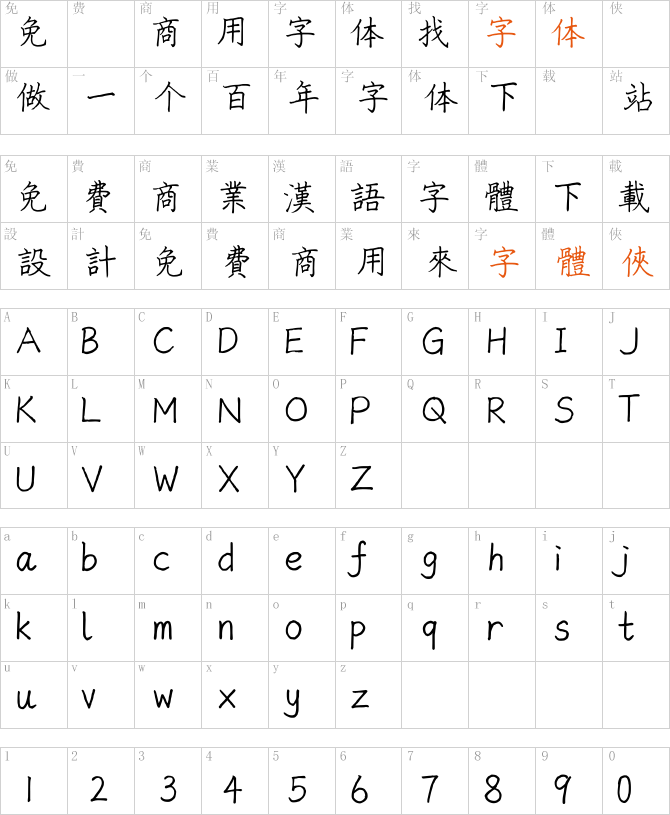
随峰体_免费可商用手写体下载
随峰体:香港同胞阿坤以啫喱笔写成的手写字体 开源免费商用。“随峰体”的创作者是阿坤,一位热爱写字的香港人。“随峰体”是经过两年时间,逐字逐字以啫喱笔写成的手写字体,而且保留手写痕迹和瑕疵。早在一年前就决定以开源形式释出字体,完全免费,可以自由商用,希望大家喜欢。Beta版推出之后,会根据用家意见不断完善字体,以及统一字体风格后,再同样以开源形式推出正式版,敬请期待!